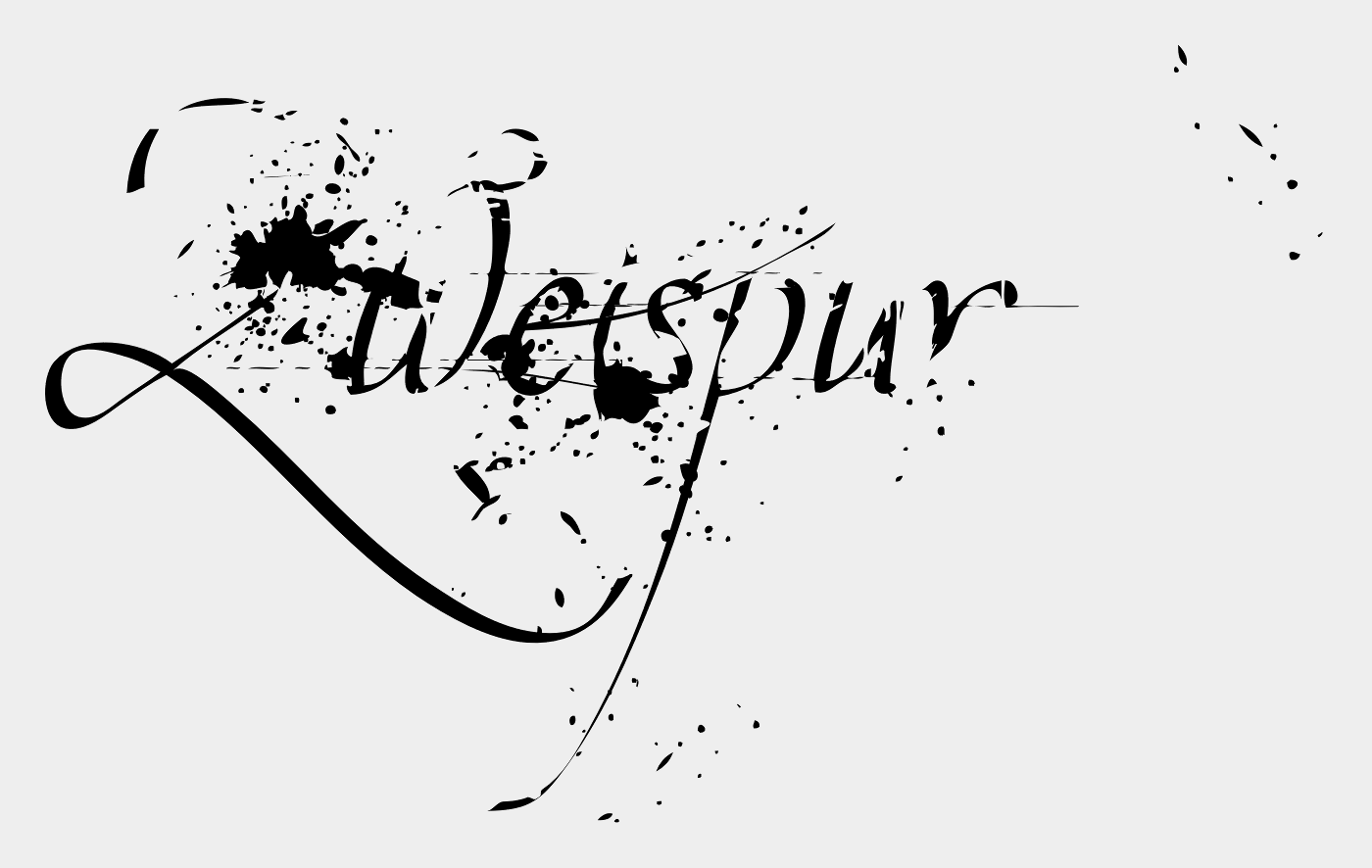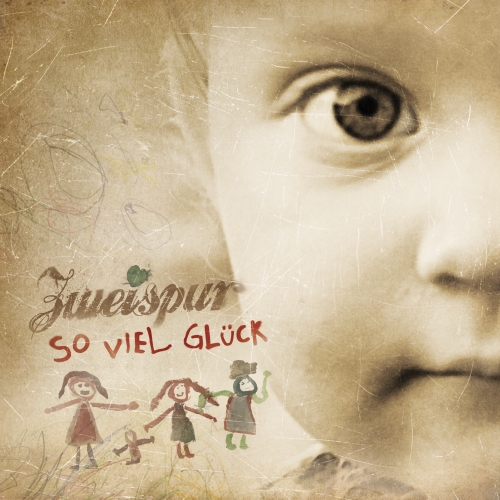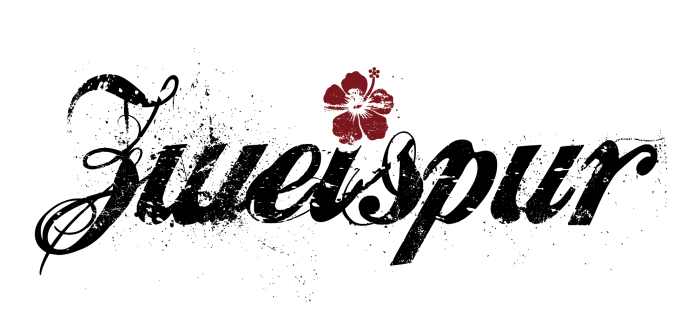
Schrift der Band "Zweispur" gesucht
Die Schrift, die ich suche, ist die, die wir in unserem Bandlogo verwenden. Sie gefällt uns sehr gut und wir würden gerne dabei bleiben. Leider können wir derzeit in diesem Stil keine weiteren Inhalte erstellen, weil wir nicht wissen, was die Designerin, die uns das Logo in 2010 erstellt hat, damals als Basis verwendet hat und überhaupt wie sie diesen Schriftzug in der vorliegenden Form erstellen konnte.
Daher meine Frage: Gibt es hier jemanden, der die Schriftart kennt? Es kann sehr gut sein, dass die Designerin ihn nicht eigens für uns erstellt hat. Sie meinte damals, dass es sich um eine "fertige" Schrift gehandelt hat.
Sind die zusätzlichen Schnörkel (z.B im "Z") und diese "grunchigen" Pixel dann einfach frei nach Gusto dort hinein gemacht?
Gibt’s auch mit Herz statt Blume :-)
Die zusätzlichen Swooshs und Störungen sind wohl von Hand hinzugefügt worden, wie es das auch bei der Valeria Cola gibt:
Sind die zusätzlichen Schnörkel (z.B im "Z") und diese "grunchigen" Pixel dann einfach frei nach Gusto dort hinein gemacht?
Die Schnörkel könnten als Vektor-Linien dazugemalt, oder Teile einer Script-artigen Schrift oder Schörkel-Dingbats sein. Ich vermute ja auch irgendwo auf DaFont zu finden, wenn man sich dort schon zweimal bedient hat. :-)
Sowas z.B.: http://www.dafont.com/de/mathilde-castleland.font *
Bei dem Dreck vermute ich Photoshop, den Schriftzug habt ihr ja anscheinend nicht als Vektor-Datei vorliegen.
Gibt’s auch mit Herz statt Blume :-)